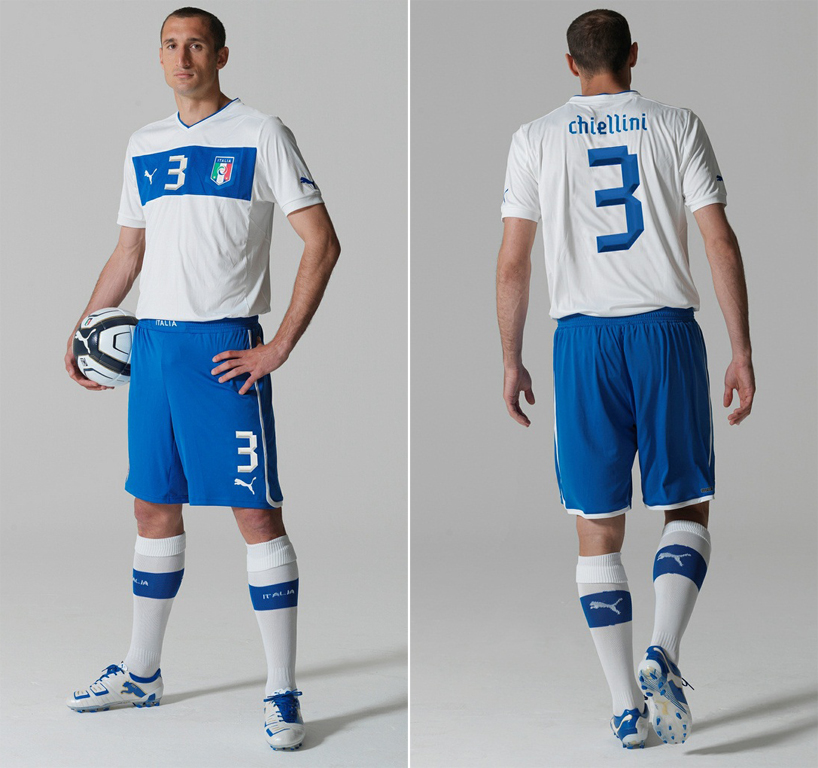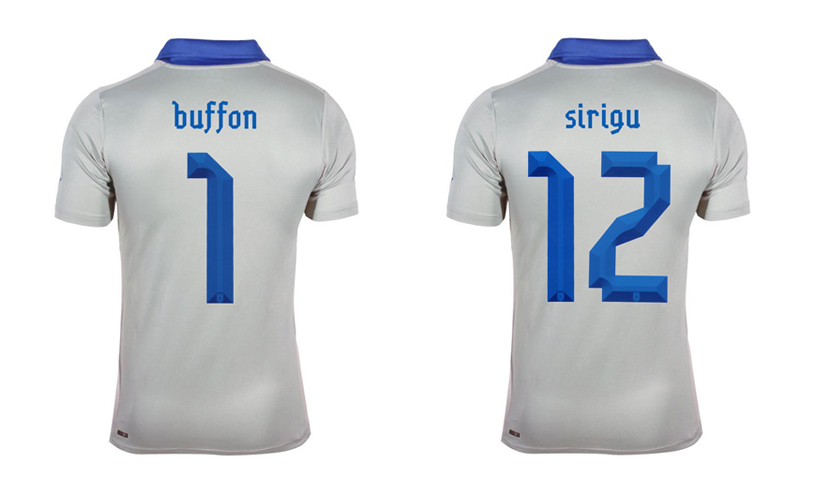
Ora che sono finiti gli Europei di Calcio, possiamo finalmente tornare a parlare di cose serie.
Come ad esempio le divise della Nazionale Italiana e la scelta della font.
Le nuove maglie dell’Italia indossate nell’Europeo 2012 e griffata Puma hanno un look vintage, ufficialmente denominato stile “future-classic”, e si ispirano a un modello storico, utilizzato più volte dall’Italia nel 1950, partita Italia-Rappresentativa Lionese (la fascia nera sul braccio era in segno di lutto per ricordare la tragedia di Superga del Grande Torino) e nel 1974.
Tutto lo studio del design è a cura di GBH – Gregory Bonner Hale, un’agenzia con base a Londra che nel 2005 ha realizzato anche lo stemma della FIGC – Federazione Italiana Giuoco Calcio.
Ma non è tanto di questo di cui vogliamo parlare – soprattutto non voglio entrare in ulteriori polemiche per un logo italiano realizzato non in Italia – ma è della scelta della font utizzata per la maglia della Nazionale di Calcio Italiana a cura della stessa agenzia londinese.
Infatti la GBH ha realizzato per Puma l’esclusivo font “Gaffer“.
Per la realizzazione di questo carattere l’agenzia si è ispirata alla campagna Make Football Anywhere dove del nastro adesivo viene usato per improvvisare porte e campi di fortuna per giocare a calcio.
Il nome viene infatti da Gaffer Tape, un’azienda che produce il nastro adesivo telato nero, quello usato prevalentemente dagli elettricisti.
Il risultato è un carattere interamente composto da nastro da elettricista, che si distingue in campo per la sua leggibilità e chiarezza.
Per la sua realizzazione sono stati acquistati 150 rotoli di nastro adesivo nero per sperimentare le varie combinazioni di aste, occhi e grazie, e solo appena raggiunte le giuste proporzioni è stato sviluppato l’intero alfabeto romano, con numeri e accenti europei, e successivamente digitalizzato.
I numeri sulle maglie sono una declinazione della font in 3D, disegnata esclusivamente per la Nazionale Italiana.
Sinceramente questa scelta ha lasciato me e altri colleghi abbastanza perplessi.
Ecco alcune delle critiche raccolte in rete:
- Leggibilità e chiarezza: vedere la font “esplosa” in tutti i suoi caratteri si percepisce il gioco e la leggibilità, mentre in campo, soprattutto per la leggibilità dei nomi c’è stato qualche problema (forse a causa dell’uso del minuscolo, o per una leggera sfumatura del bianco…).
- Nastro adesivo: a un primo sguardo, l’effetto “nastro adesivo” non era così immediato, ma l’impressione era di una font quasi gotica, medievale, forse anche a causa di quelle grazie così squadrate che sembrano disegnate con un pennino spesso.
A discapito del titolo del post, questo non vuole essere un vero e proprio processo, ma avrei piacere a sentire altre voci in merito.
Grafici e designer, voi che ne pensate?
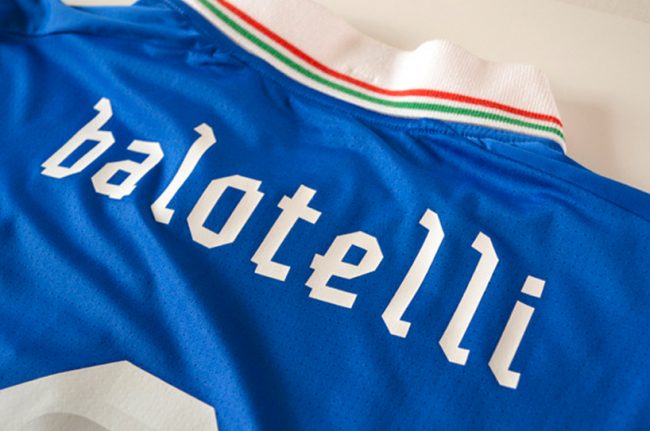
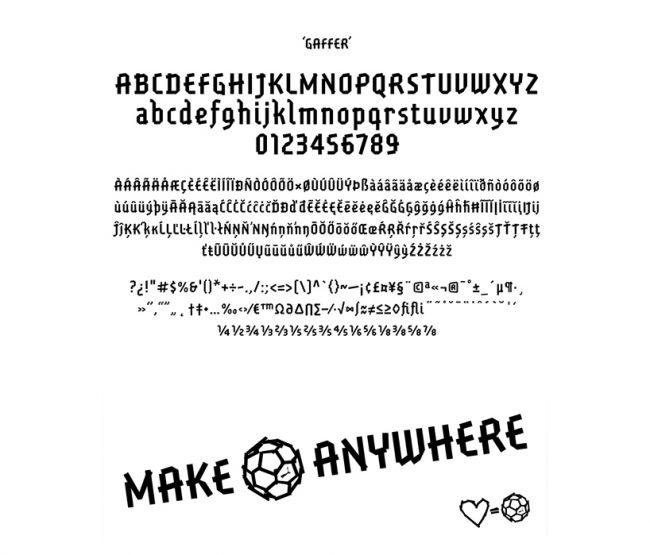
mah… io lo trovo dozzinale.
ma vogliamo parlare del colletto che porta la bandiera invertita?
sui numeri il gaffer poteva anche starci. sui nomi: da vicino inguardabili, da lontano più leggibili, gli angoli diventavano curve. praticamente inutile l’effetto tape.
Mai visto nessuno tagliare lo scotch a 45° per fare una lettera: quindi la premessa è disattesa nello svolgimento. Nel complesso il risultato mi pare incomprensibile.
Oggi ho scoperto che la font Gaffer è utilizzata in molte delle Nazionali sponsorizzate dalla Puma, e che non tutti hanno gradito…
Michelangelo Caruso
E’ inutile l’effetto nastro adesivo se poi la font viene stondata…
In realtà quello utilizzato dall’Italia per i numeri è differente da quello utilizzato dalle altre squadre: ha le linee verticali e orizzontali perpendicolari anzichè oblique e inoltre ha un effetto rilievo. Inoltre alcune squadre lo utilizzano con le iniziali maiuscole, altre no (come l’Italia). Ho scritto due parole al riguardo http://www.7football.it/2012/02/22/italia-home-euro-2012/